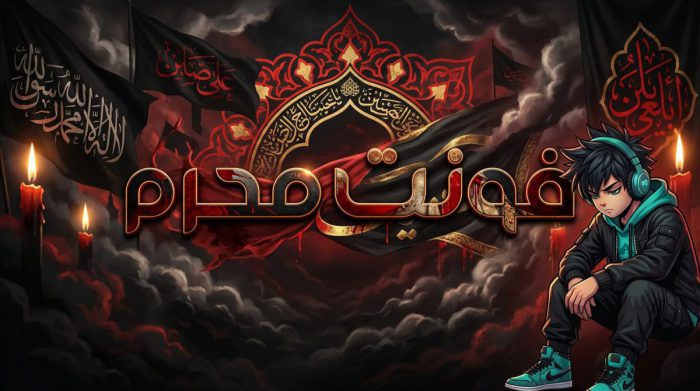
مجموعه فونت محرم (۶ فونت فارسی)
با مجموعه ۶ فونت محرم، به سادگی به طرح های گرافیکی خود حال و هوای معنوی و اصیل ببخشید. این پکیج که برای نیاز طراحان در ماه محرم و سایر مناسبت های مذهبی گردآوری شده، شامل فونت هایی با ساختار سنتی و رسمی است که برای ایجاد پوستر، بنر، کتیبه و تایپوگرافی های عاشورایی ایده آل هستند.
این مجموعه با الهام از خوشنویسی سنتی و خطوط ثلث طراحی شده و ترکیبی از زیبایی و خوانایی را ارائه می دهد.
برخلاف بسیاری از فونت های رایگان که تنها یک وزن دارند، این پکیج با ارائه وزن های مختلف (ضخیم و نازک)، دست شما را برای تایپوگرافی های حرفه ای و ایجاد سلسله مراتب بصری باز می گذارد. تمامی فونت ها دارای حروف و اعداد فارسی کامل هستند و به راحتی بر روی تمام سیستم عامل ها نصب می شوند.